脑洞不够大,就别想看明白这些字体设计
你是否也曾尝试用“打卡”的方式,在一段时间里坚持连续的设计创作?若这种“每日设计习作”变成了比赛,风格各异的设计师们将碰撞出怎样的作品呢?
通过每周或每日设计一幅作品,以锻炼自身技能和积累灵感,这样的项目在设计行业并不少见。又一山人曾每周设计一张海报,创作了《每周出海》系列;美国设计师Mars Maiers则连续1000多天不间断,坚持每日设计海报......而两位来自巴塞罗那的设计师Nina Sans和Rafa Goicoechea则决定,将这种个人练习变成一项年度字体设计比赛——“36 Days of Type”。
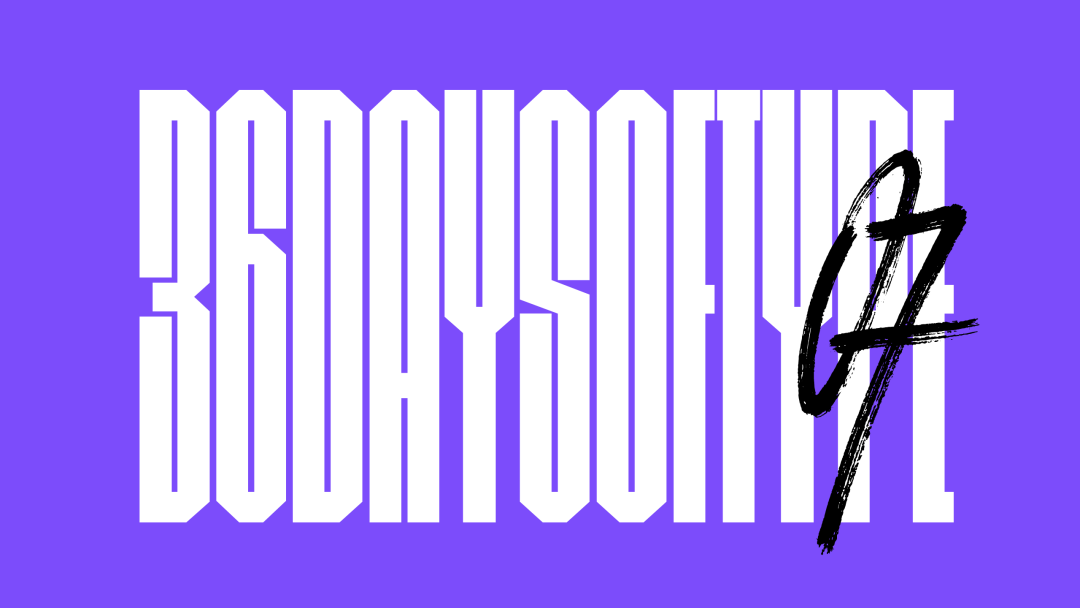
2014年,Nina和Rafa在Instagram上发起了“36 Days of Type”项目。他们每年都会邀请全世界的设计师、插画师和字体设计爱好者们在36天里,按照规定日程,设计A到Z、0到9这26个字母和10个数字,并将作品上传到Instagram上。
2020年第七届“36 Days of Type”项目日程(3月2日-4月6日)
2019年设计师在Instagram上传作品参加此项目的示例
2019年正值项目发起的六周年之际,Nina和Rafa决定与Adobe合作,在众多参赛的字体设计中选出六组最优秀的作品,并赠予它们的创造者为期一年的Creative Cloud订阅套餐。这六位设计师和艺术家分别是:Julie Featherstone、Lewis MacDonald、Shakthi Hari N V、Jess Ebsworth、Liam Bevin和Zai Divecha。
Design360°将会为大家分享他们的获奖设计作品,以及平面设计师与评论家Yves Peters在Adobe Blog上对他们的介绍。
Julie Featherstone
英国,伦敦
Julie是伦敦奥美的设计师,平时在业余时间进行个人插画与艺术创作。她毕业于中央圣马丁艺术与设计学院,在设计实践中对插画和字体越来越感兴趣。在18年来的设计工作中,她也成功地将插画和文字排版应用到部分客户的设计项目中。
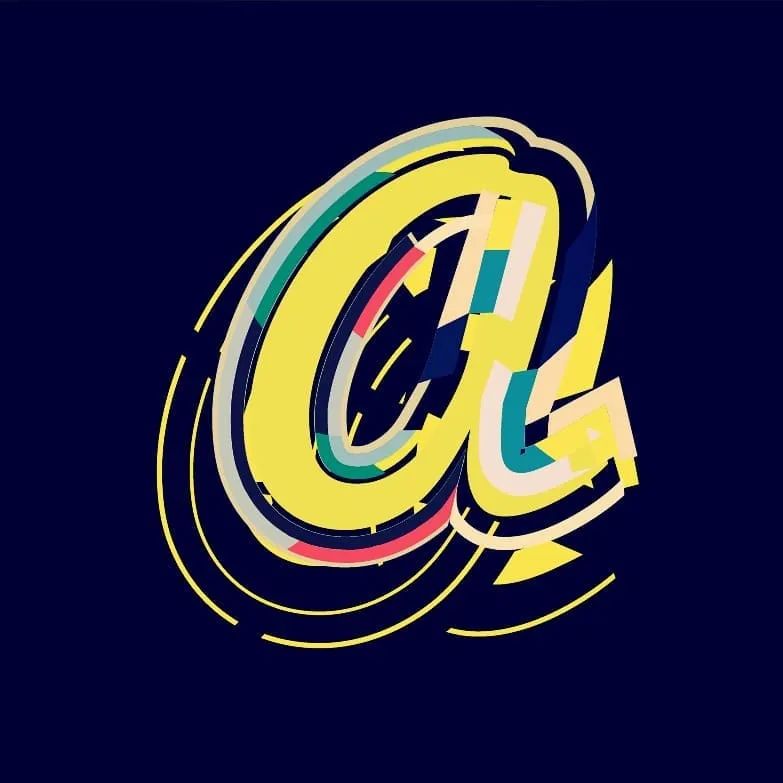
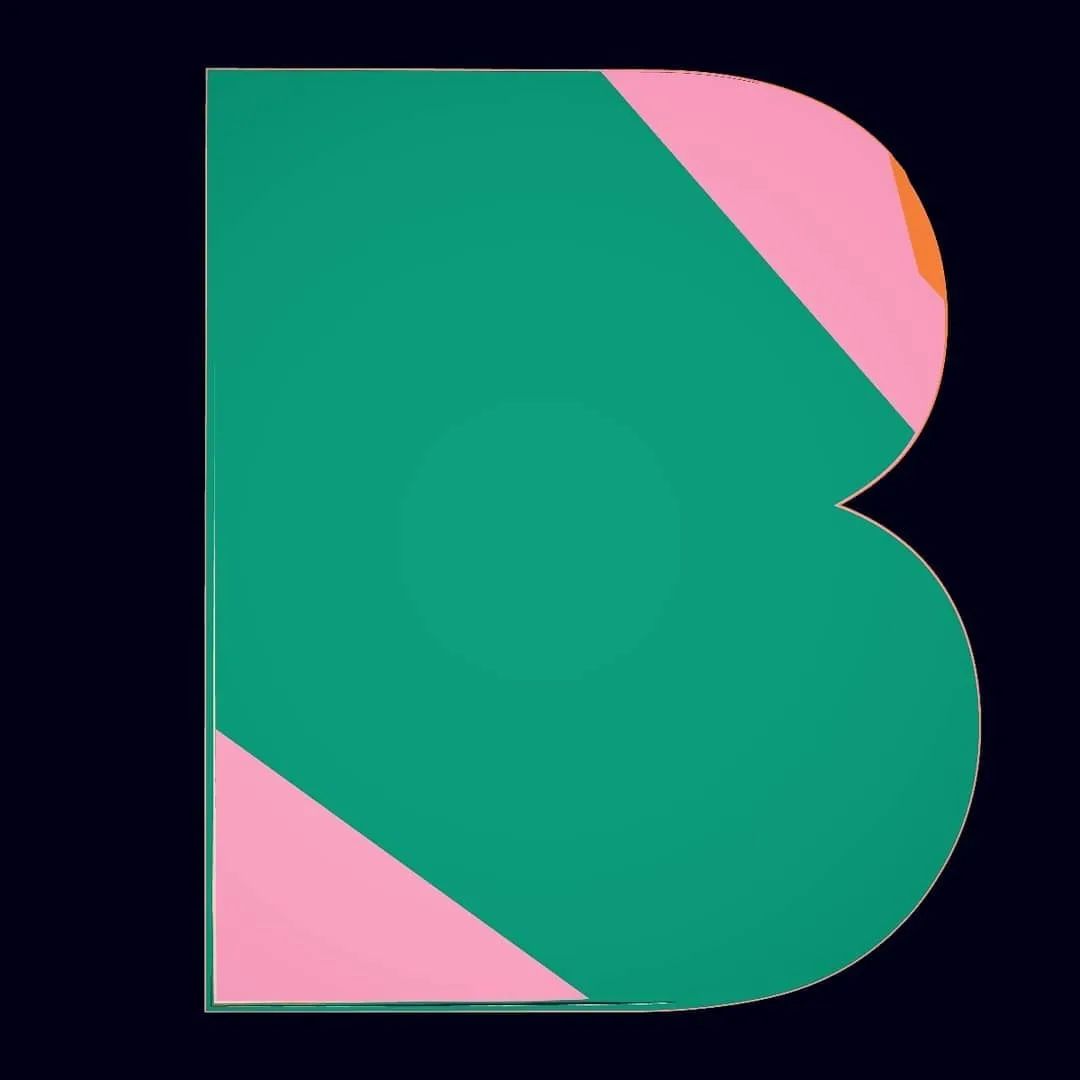
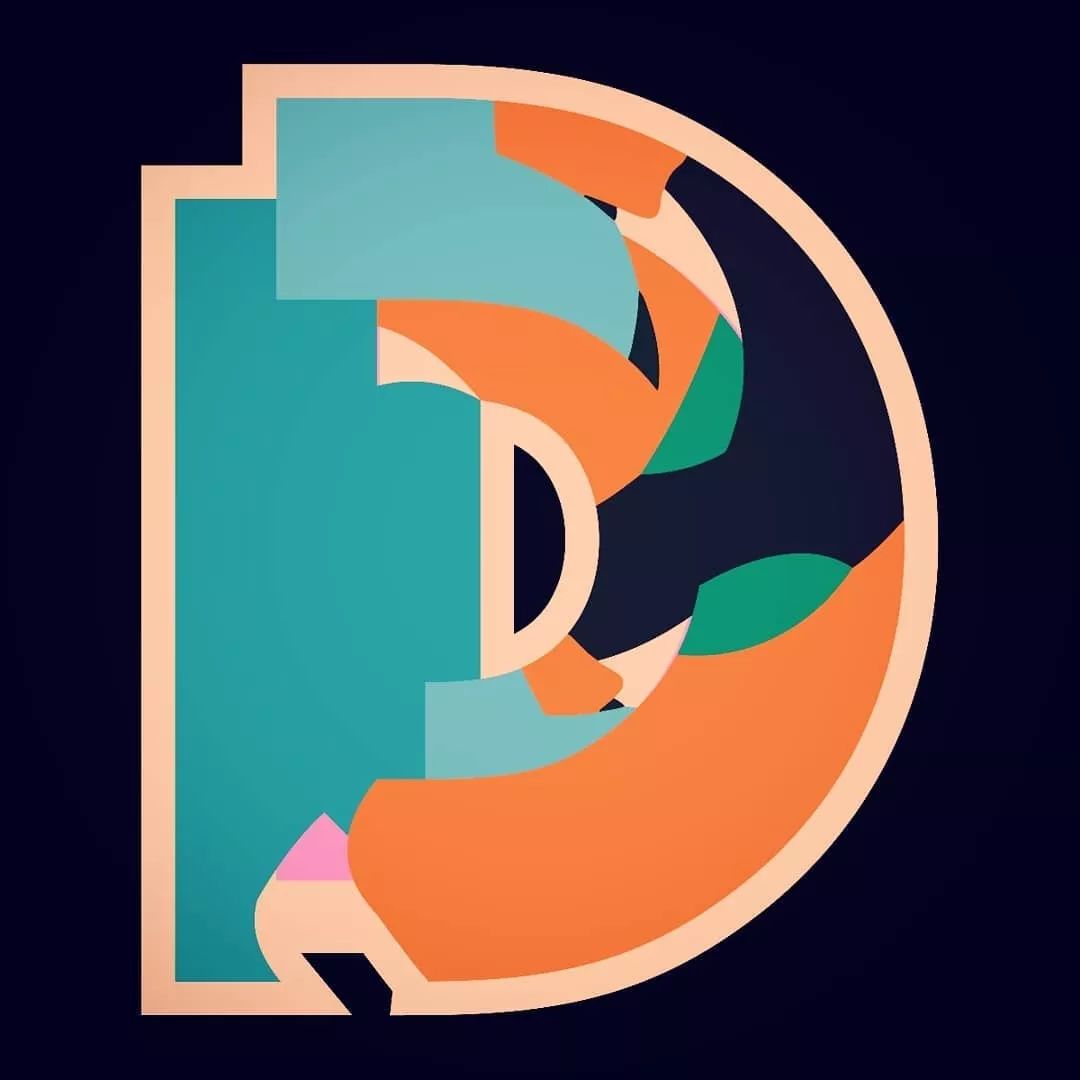
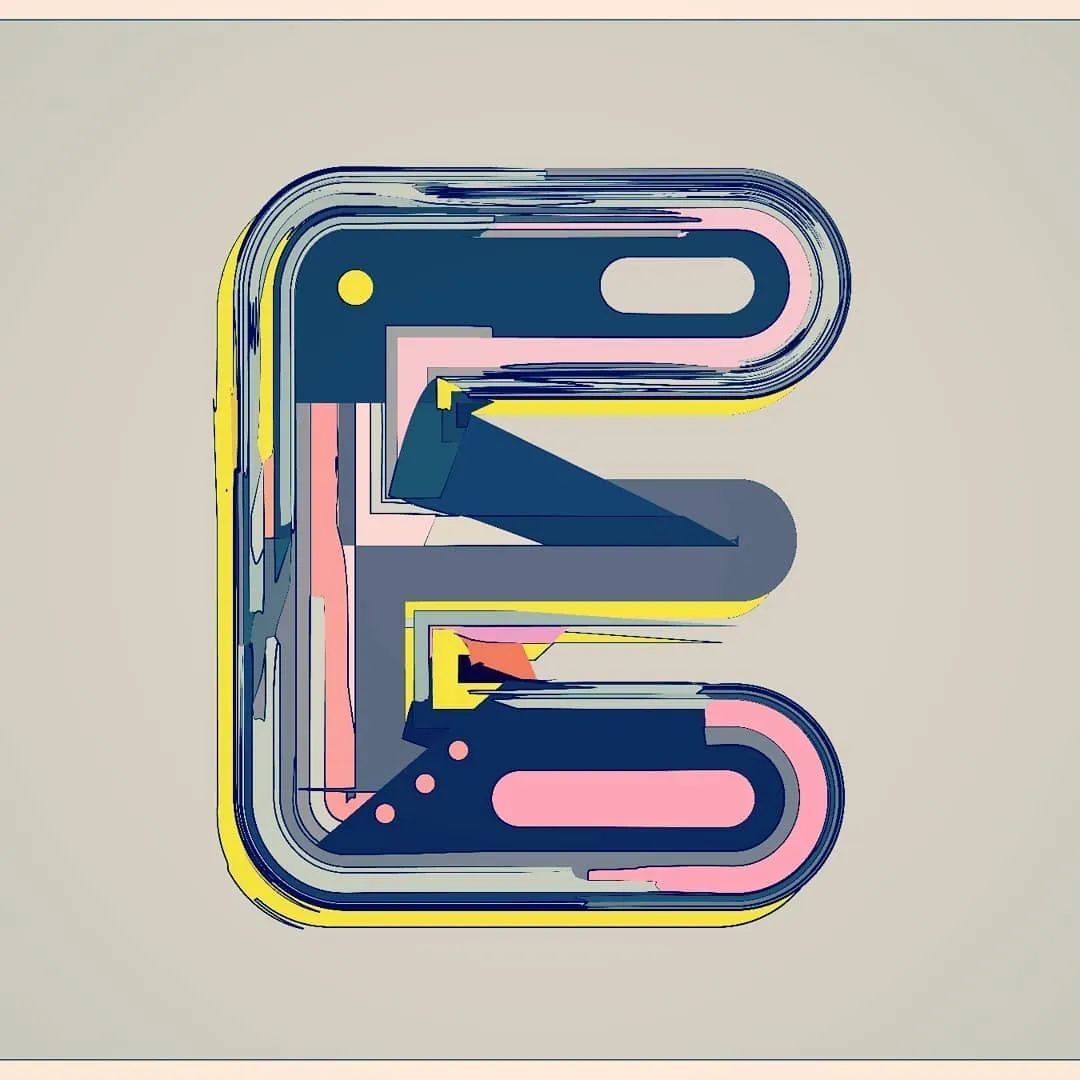
近年来,她学会了在AI中创建自定义矢量笔刷,并应用到自己的字体创作中。Julie表示这需要大量的实验,并对图层、宽度、颜色和亮度进行微调。
Julie在Instagram上关注“36 Days of Type”很长一段时间了。去年,她决定和几位同事一起参加比赛。“我们相互鼓励,继续前进,每天督促自己创造一些新的东西。我也很喜欢我们每个人有不同的风格。”
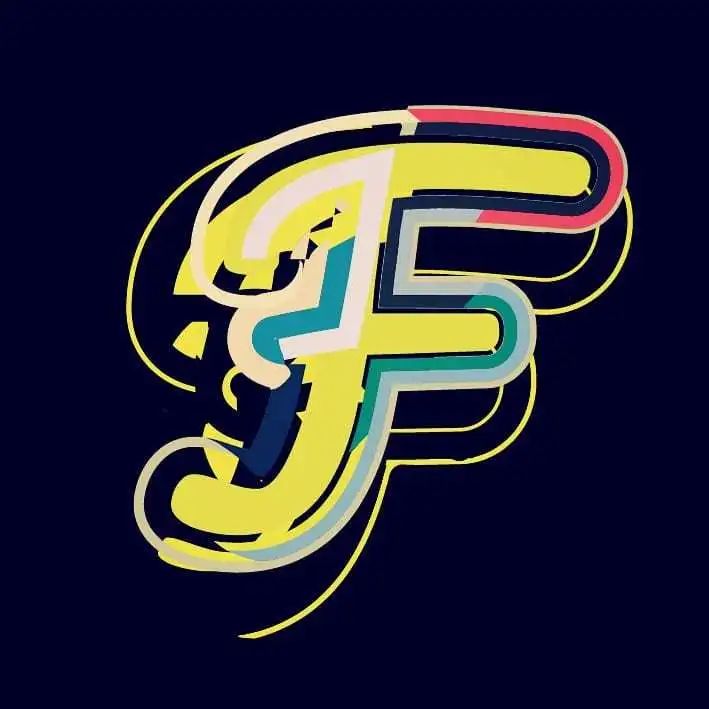
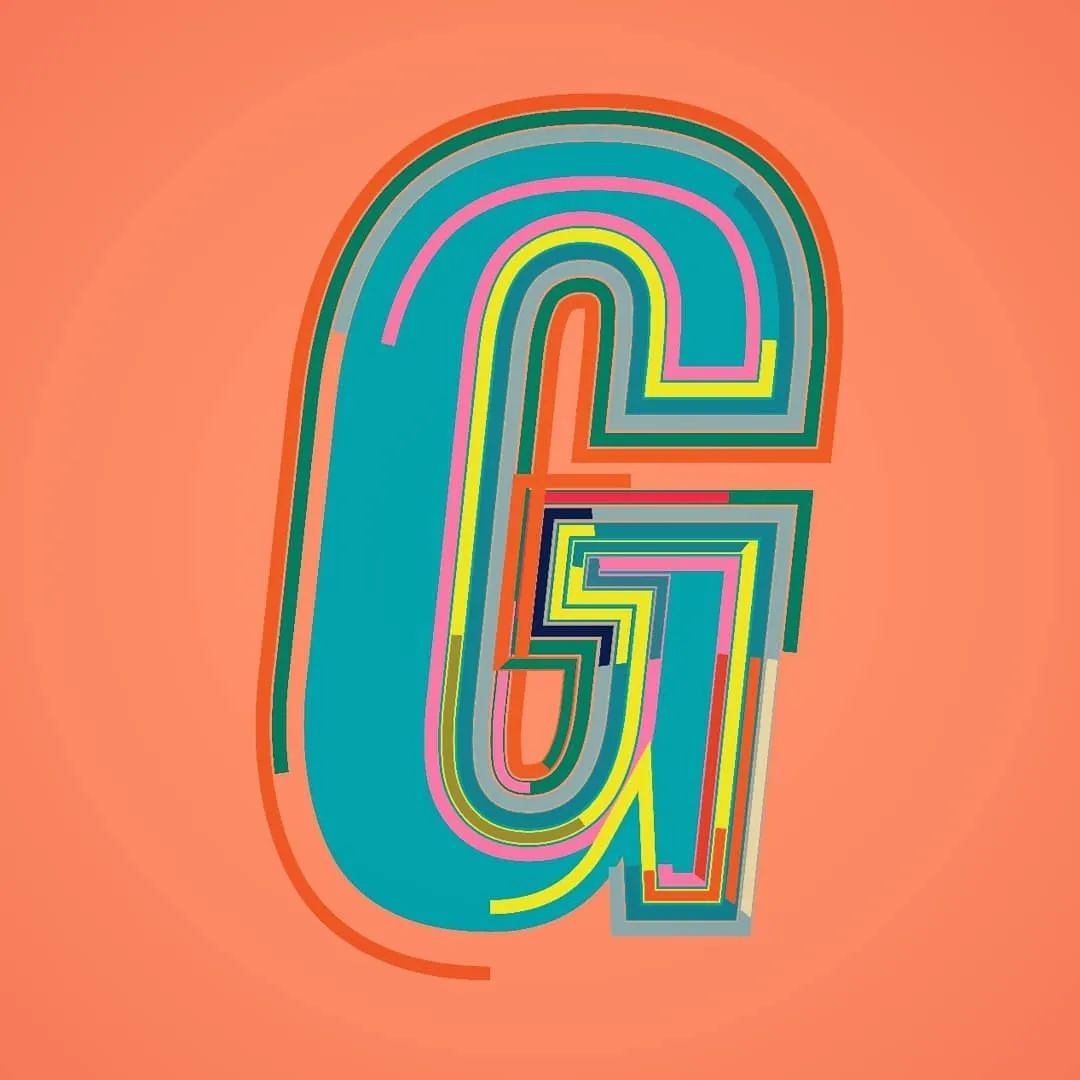
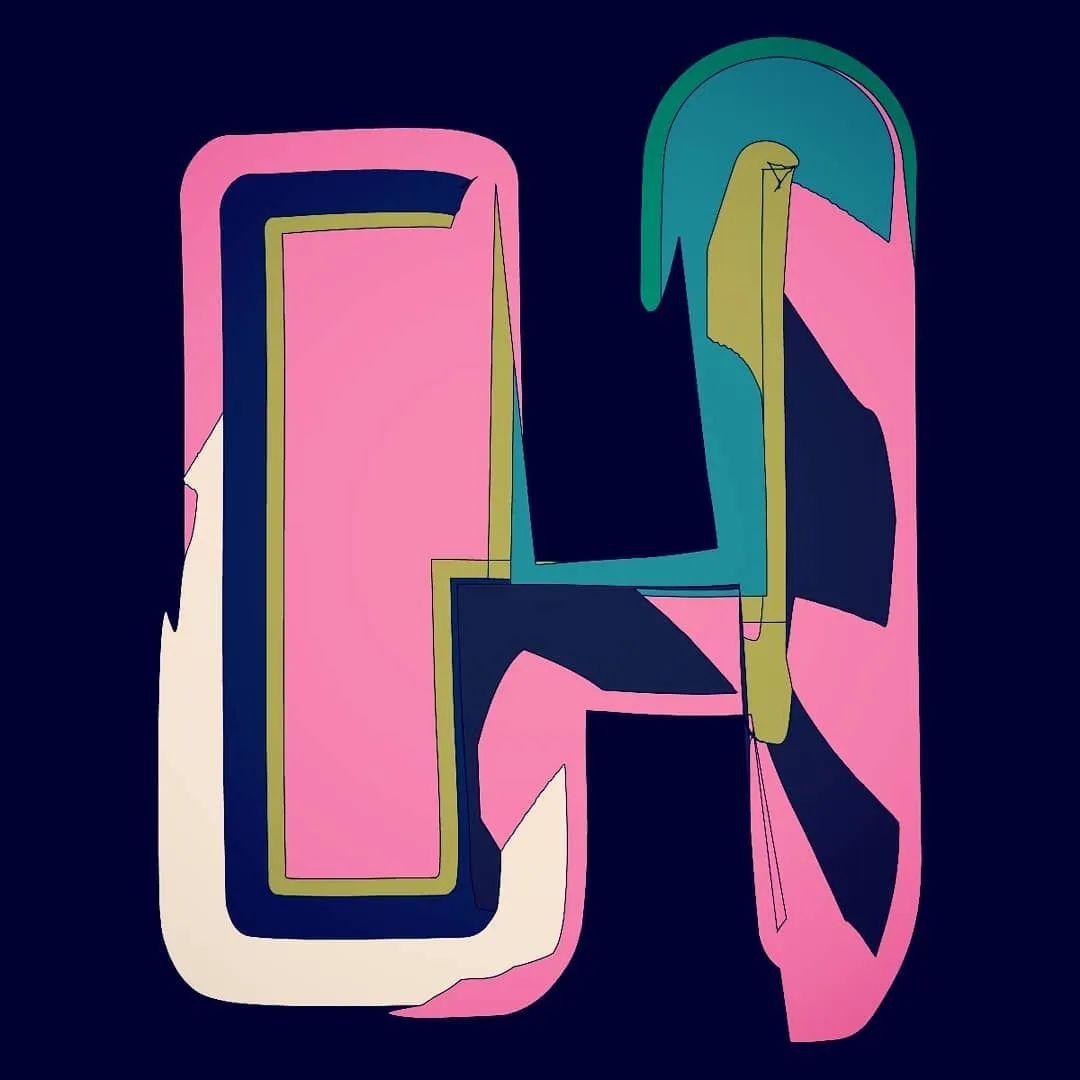
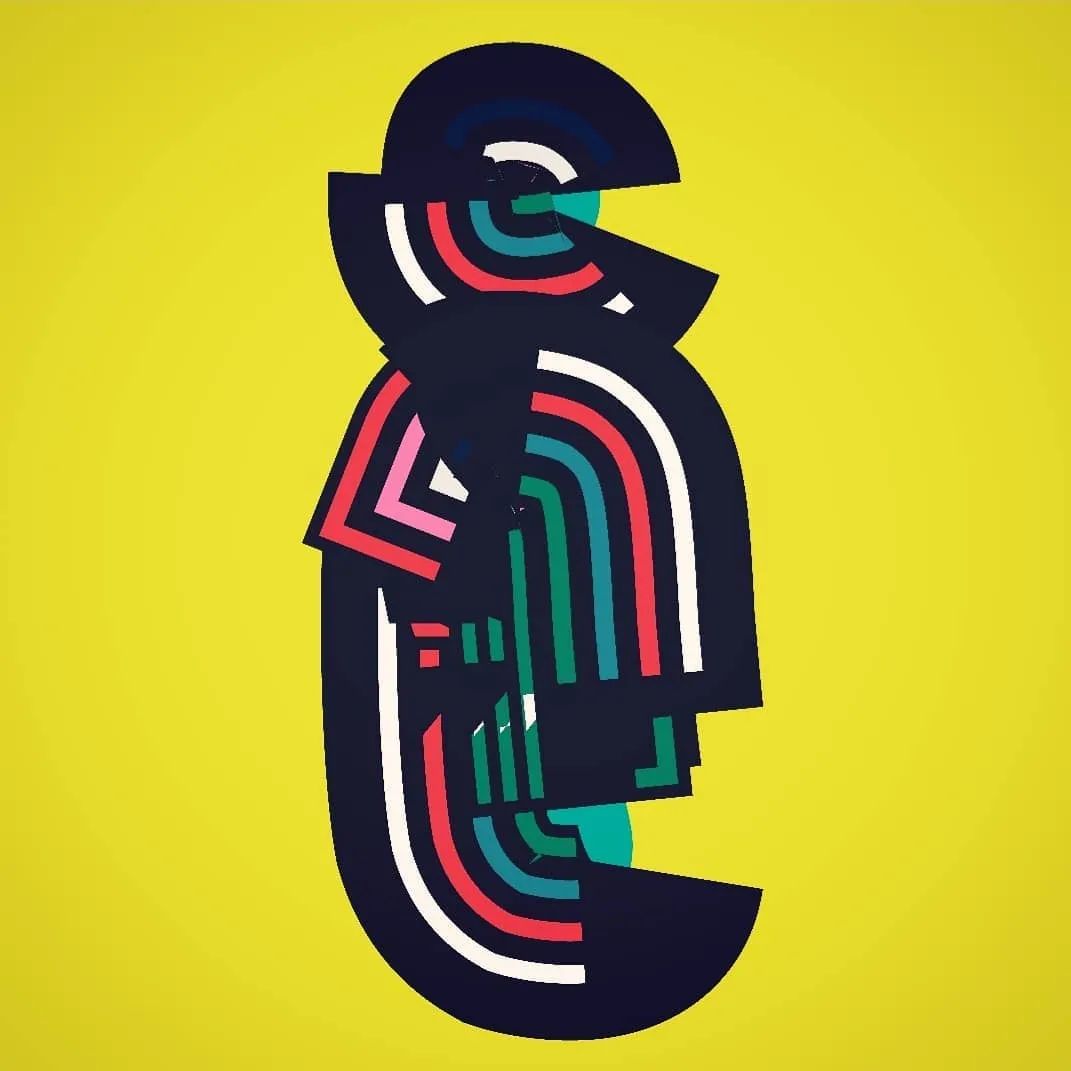
Julie对每个字体的构思都是和她当时的心情互相对应的。另外,她也会在创作时发现一些从未用过的新设计技巧。例如,在设计“L”时,她发现可以在PS中将字母设计成立体图形。
有时她能直接将想到的创意方案勾画出来,但大多数情况下都会从某幅图像或是一组颜色开始,然后慢慢激发自己的灵感。“一开始,我不敢相信自己赢了,尤其是和这么多精心设计的作品竞争。”想到自己的获奖,Julie很开心,“结果公布时,办公室里的同事都为我欢呼,太棒了!”
Lewis MacDonald
英国,苏格兰格拉斯哥
Lewis的字体设计是经由他的独立字体设计工作室Polytype平台发布的。在大学时期,他经常为学校的音乐舞蹈活动设计海报和宣传单,并渐渐开始关注好看的、优秀的字体,并能轻易识别出很多字体。他一心想创造属于自己的字体,甚至连期末考试也考砸了。
Lewis把每个字母或是数字的设计都看作一个新的挑战。每一天,他都会信手涂鸦脑海里出现的任何想法,慢慢完善并探索出一堆变体,然后从中选择一个最喜欢的样式。他有时会错开连续的线条(如“F”),或是将字体中的连接线缩小(如“M”和“U”)。“画这些图形,想清楚如何把所有元素像拼图一样组合在一起,是一件让人十分愉悦而满足的事情。”
这是Lewis第三年参加“36 Days of Type”了,但却是第一次完整地完成了整个挑战。当他看到Instagram上有其他人再上传了第一天的字体设计时,才意识到这个挑战已经开始了!
有了以往的经验,他明白如果自己错过了一次日常更新,整个进度就会落后,然后失去完成整个系列的动力。“虽然有几天很难做出自己满意的作品,但整体而言,整个挑战进展得还算顺利,我总能想出一些自己真正喜欢的东西。”
Shakthi Hari N V
印度,泰米尔纳德
Shakthi Hari N V是一位自学成才的平面设计师和插画家。他来自印度泰米尔纳德绑一个叫Jayankondam 的小镇,在大学自学了Photoshop、Illustrator和其他Adobe工具。Shakthi曾就读化学工程,也做过商业技术分析师的工作。后来逐渐意识到创意和艺术创作才是自己真正想做的事情。
这是Shakthi连续第三年参加“36 Days of Type”挑战了,“我从大学时就知道了这个项目。当时我在Instagram上寻找灵感,注意到几个令人惊叹的设计作品,下面都附带了这个标签。”他过去没有专门研究过字体字形,在文字排版设计方面的知识有限。因此,他决定用“负空间”的手法来创造字母和数字,而不是直接设计一套全新的字体。
“负空间”手法的使用,使Shakthi很容易设计具有对称性的字体,但要设计具有锐利边缘的字母和数字却比较困难,最后他本人最喜欢的也是0到9这10个数字插画。
在创作时,Shakthi会先用传统方法画出作品的草图,然后再导入到电脑中,丰富其中的细节。在保持全职工作的同时进行36天的挑战,这对Shakthi来说是有一定难度的,“有时候我真的想放弃,但在一个月里连续每天都创造一些新东西,能带给我愉悦和满足......而每天创作这些插画也会让我的心情变得平静。”
Jess Ebsworth
英国,伦敦
Jess Ebsworth在2015年毕业于曼彻斯特城市大学艺术和人文学院,随后的两年曾为啤酒品牌Plato Brewing设计包装,并为英国各地的俱乐部之夜设计海报。她也签约了插画公司Roar Illustration Agency,因此接触了更多客户。
Jess不是很懂文字排版,但她很喜欢用插画的方式去创作字体。而且她的设计生动有趣,展示了自己独特的视觉语言。2018年参加“36 Days of Type”时,她只创作了一部分字母,但却受到广泛好评。因此,她决定在2019年完成所有的字母和数字设计挑战。
Jess希望每个字母或数字都有独立的风格,同时插画本身要和当天的字母或数字相关联。例如“D”代表DJ,“N”代表“Noodle(面条)”。
Jess不会在创作的一开始就想好一个特定的单词。她通常会先画出基本的字符形状,然后在AI中胡乱图画,搭配不同的形状和颜色。在这个过程中,好的创意就会慢慢浮现于脑海,“总体来说,整个设计历程是一次对创造性思维的锻炼,它真的让我找到了很多解决问题的新方法。”
Liam Bevin
英国,伯明翰
19岁的Liam Liam去年从英国伯明翰的艺术教育机构FEED Studio毕业。他没有继续深造,而是作为自由职业者参加一些MV制作等设计项目,并运营几个YouTube。
Liam第一次参加“36 Days of Type”是在2018年,但当时并未投入太多精力。聊到字体设计,Bevin说:“我除了在大学里创作过一套字体,也并没有其他太多的经验,但这让比赛变得更有趣!”在2019年的比赛中,他以一种更轻松的方式完成了这套设计,“我觉得让自己开心和发挥创意是最重要的,并不会为了快速完成项目而给自己施加压力。”
Liam把比赛当做一个尝试新风格的机会。每个字母或数字的设计都会从一个主要的立体块开始,比如一个长条圆柱体,而后再以此为主要焦点,围绕这个主体搭建其它的立体块。Liam需要尽力让整个结构不会在手机上看起来很杂乱,“我希望各个立体块间都能保持平衡,同时让人们觉得这些字体都像真的存在于现实中。”
Liam也尽力保证每个字母或数字的可读性。“有时候,我会意识到设计的草稿和数字、字母并不相似,或者整体重量感和平衡感的效果不好。这种情况下,我会离开几分钟,然后带着新想法回来再试一次。”
Zai Divecha
美国,旧金山
旧金山的纸艺艺术家Zai Divecha将36个字母和数字设计成了几何纸雕塑和大型艺术装置。当时,是一位连续三年参加“36 Days of Type”的插画设计师朋友向她提起了这个项目。
虽然比赛即将开始,留给Zai准备的时间所剩无几,她还是决定要全身心投入到项目中去,“我确定了这次设计中所需要的元素和材料——白纸、胶水、5×5寸的底板卡片等,并想好如何拍摄这些作品,然后就开始这场比赛了。”
除了在大学上过一堂字体印刷课外,Zai 从未认真学习过或尝试过字体设计。因此,这不仅是Zai首次参加“36 Days of Type”,也是她第一次专门研究字体的设计创作。
“那时,我尝试了折叠、卷起、撕裂、戳洞或切割等各种纸艺技巧,并将此作为设计字母和数字的基础概念。”Zai回忆道,“一旦发现了一种我喜欢的新图案模式或制作技巧,我就会想办法把它变成一个字母或数字。”
在创作的过程中,Zai需要进行大量的实验,比如将纸卷成管状并切刻出小褶叶,或是揉成纸团状。这些实验也让她改良了一些常见技巧,并研究出了不少新技术。
每一件作品都需要花1至3小时进行创作,然后再用半个小时进行拍摄和后期制作。Zai偶尔能一次性创作3-4个字母数字,但大多数时候都是在最后一分钟才完成当天的作品。她之所以能坚持下去,是因为从参加比赛的设计师和粉丝那里得到了很多鼓励和支持。而这个项目中的一些作品也成为了她后续大型装置作品的创作灵感。